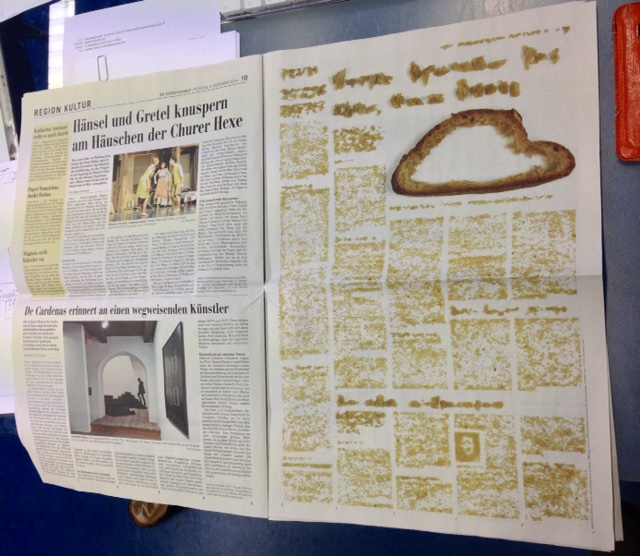
eine wahrhaftige «brotschrift» überraschte mich heute von der zeitungsseite der «die südostschweiz». im rahmen des kunstprojekts «ortung» platzierte die künstlerin isabelle krieg (dresden, zürich) dieses werk. diese «brotzeitung» sei eine schlüssige interpretation einer tageszeitung, denn auch diese sei tägliches brot, schreibt das blatt …
Vielleicht, bevor die Maus dran war …
wen meinst du mit die maus? sie?
Lach! So eine Despektierlichkeit käme mir nie in den Sinn! Nein nein, ich dachte schon an so ein kleines nettes Pelztier, das gerne Brot futtert.